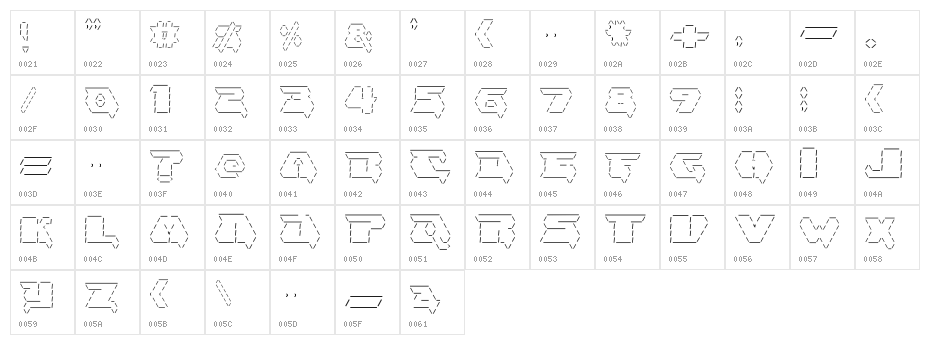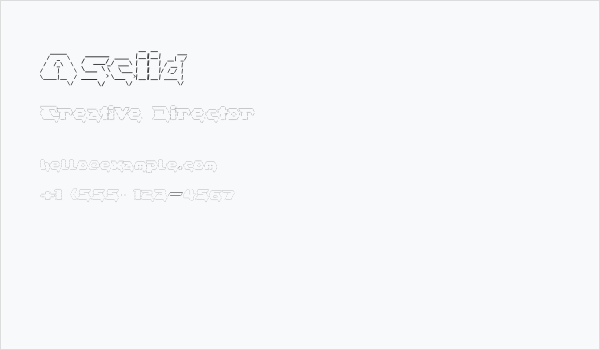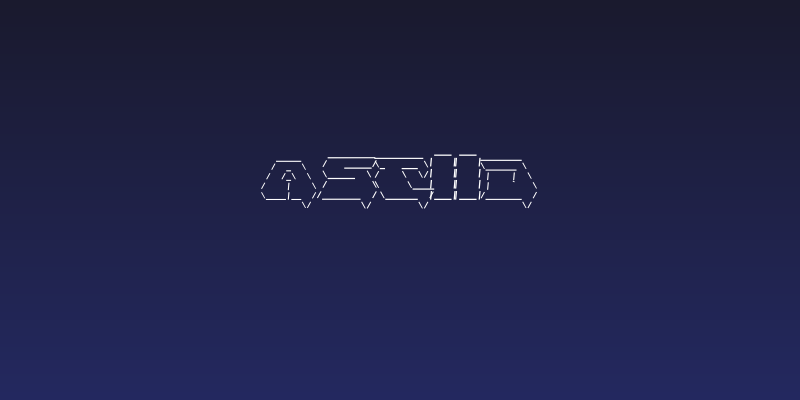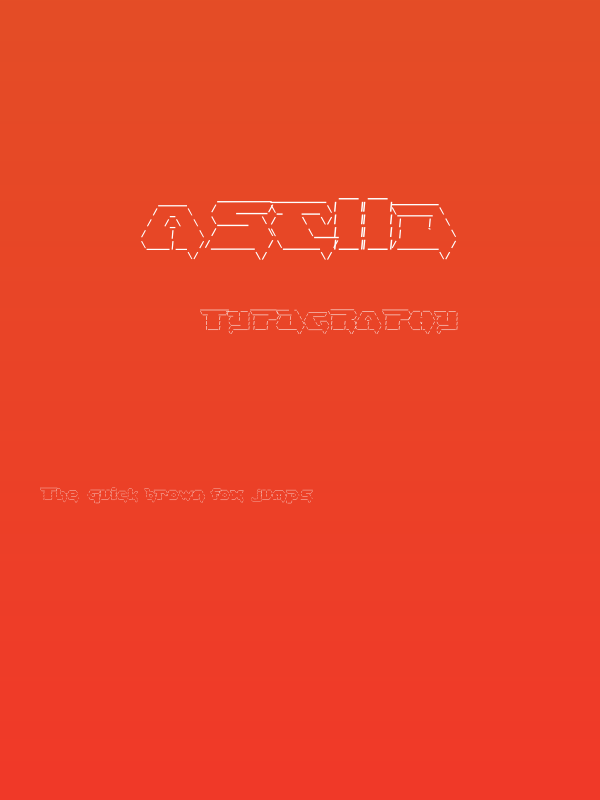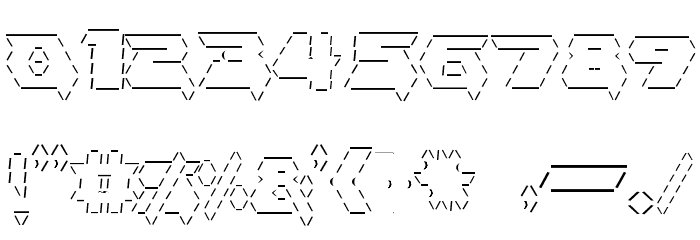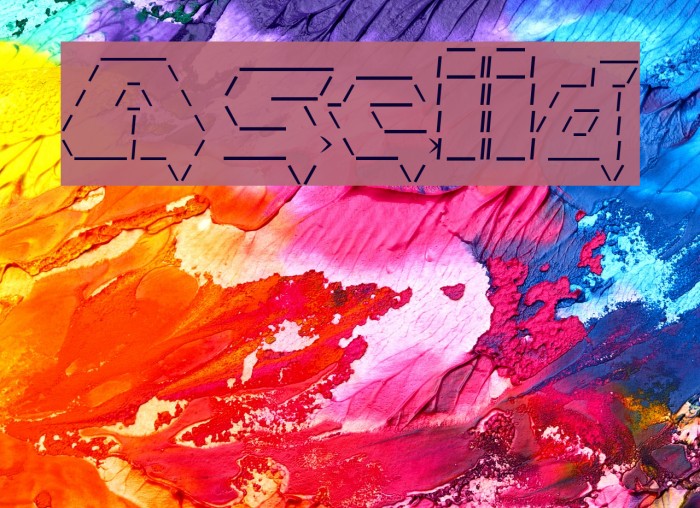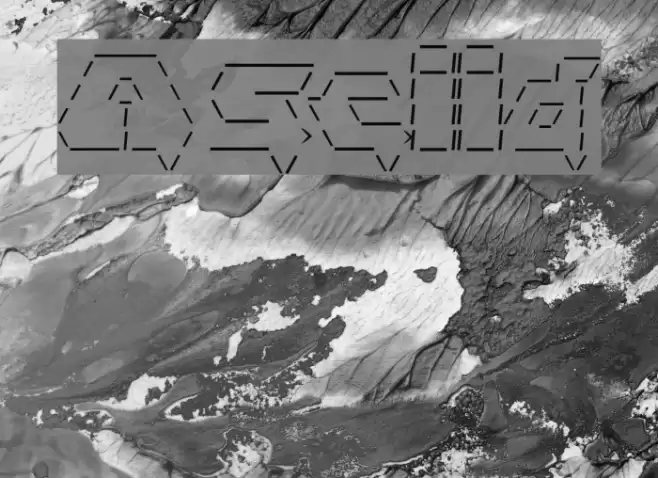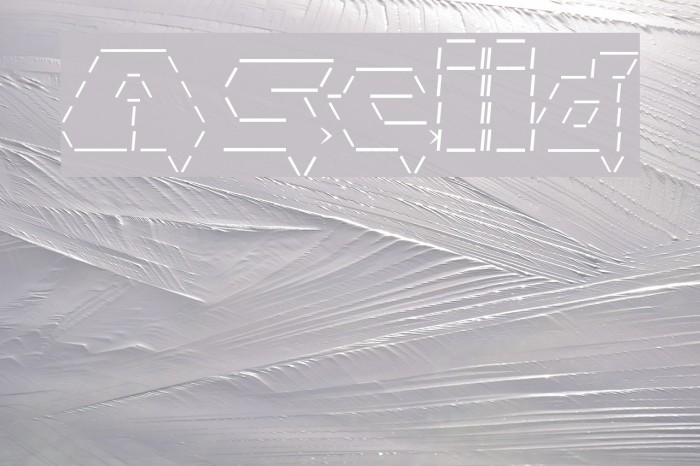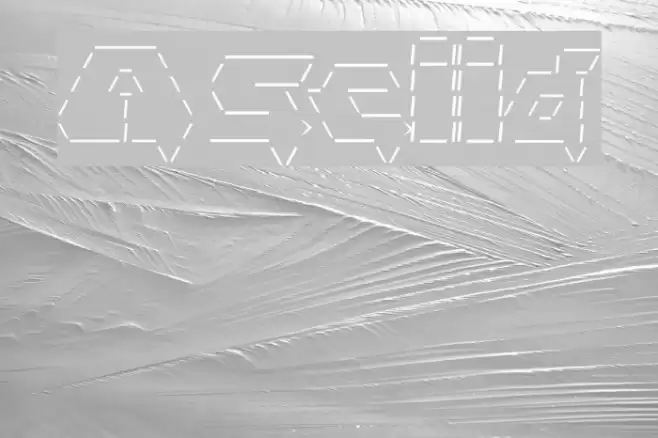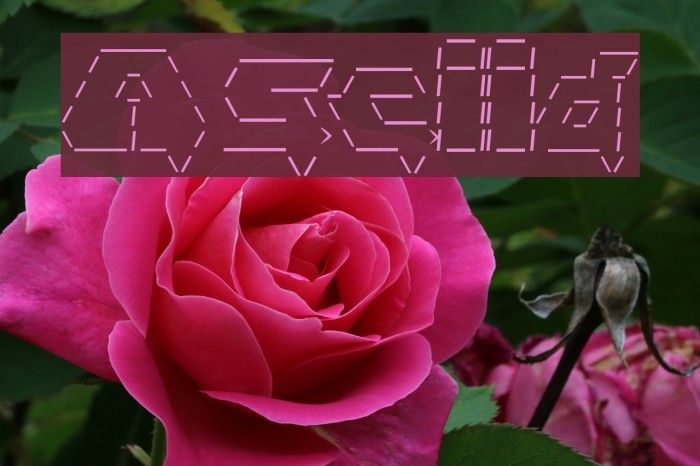
Asciid Font
| Kategorien | Futuristic |
| Gesamtstil | Futuristic, Digital |
| Anwendungsfall | Logos, Posters, Digital Art |
| Vorgeschlagene Projekte | Ideal for digital art projects, tech-themed posters, or creative coding displays. |